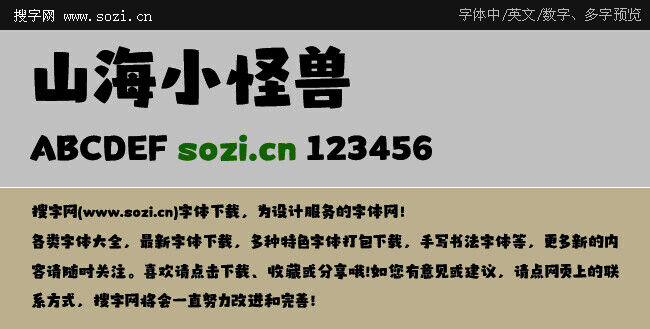
山海小怪獸
搜字網(wǎng)提供一款山海小怪獸中文藝術(shù)字體下載,山海小怪獸是一款卡通風(fēng)格字體,包含簡(jiǎn)體漢字6763個(gè)。字體童趣可愛(ài),結(jié)構(gòu)多變靈動(dòng),字形活潑清新,造型生動(dòng)有趣,具有靈活的適用性,天真俏皮又不失時(shí)尚感。適合包裝設(shè)計(jì)、海報(bào)設(shè)計(jì)、廣告設(shè)計(jì)等應(yīng)用。